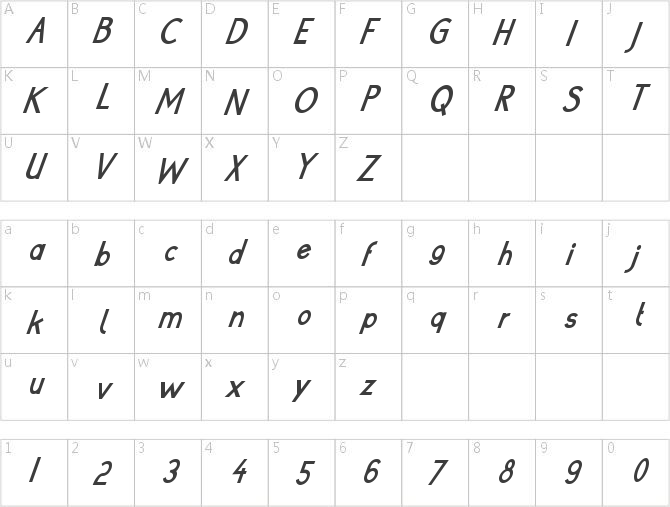
poor weekdays bold italic
poor weekdays bold italic字體字庫(kù)是一款讓人賞心悅目、百看不厭的英文字體,適合各類廣告和產(chǎn)品包裝設(shè)計(jì)應(yīng)用,字體大小0.05MB,格式為ttf字體,上傳用戶是白刃寒走得慢,作者/版權(quán)方為未知